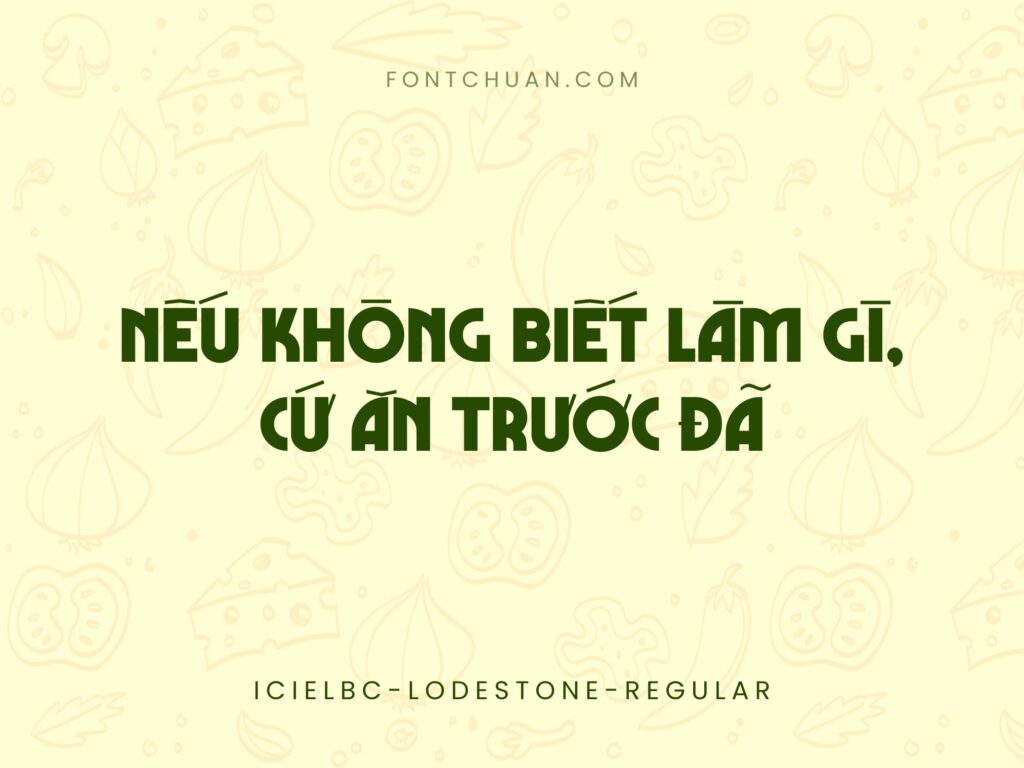
Font iCiel Bclodestone Việt Hóa
Tác giả Font: Iciel
Việt hóa bởi: Iciel
BCLodestone là một font chữ sans-serif mang phong cách cổ điển, được thiết kế với các nét chữ dày và đậm, tạo nên sự mạnh mẽ và thu hút. Font này được lấy cảm hứng từ kiểu chữ “Marvin” do Face Photosetting (London) tạo ra vào đầu những năm 1970. Để hỗ trợ cộng đồng thiết kế Việt Nam, Iciel đã Việt hóa font BCLodestone, giúp font này hỗ trợ đầy đủ tiếng Việt cùng hơn 200 ngôn ngữ khác. Phiên bản BCLodestone Việt hóa đã được thành viên Font Chuẩn sưu tầm và đăng tải, mang đến sự lựa chọn đa dạng cho các nhà thiết kế.
Về đặc điểm thiết kế, BCLodestone sở hữu các ký tự in hoa với nét chữ đậm và góc cạnh, tạo nên sự cân đối giữa tính mạnh mẽ và sự cổ điển. Font này rất phù hợp cho các thiết kế như logo, tiêu đề, biển hiệu, bao bì sản phẩm và các dự án cần sự nổi bật. Ngoài ra, BCLodestone cũng là lựa chọn lý tưởng cho các ngành nghề như quảng cáo, bất động sản, giáo dục và công nghệ, mang lại phong cách chuyên nghiệp và hiện đại. Font này cũng thích hợp để sử dụng trong các sự kiện như lễ hội, sinh nhật và các dịp đặc biệt khác.